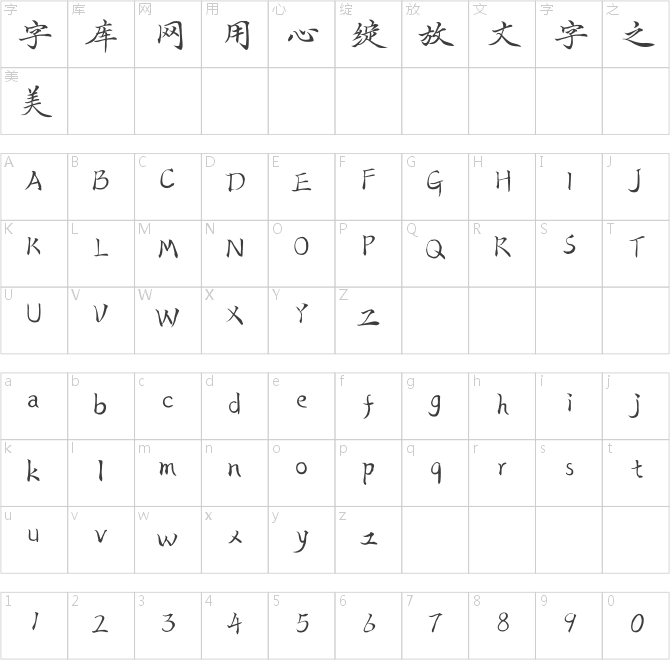
字體名稱: 漢儀常江小楷
漢儀常江小楷
漢儀常江小楷介紹
“漢儀常江小楷” 是由西安書法家協會會員、漢儀簽約字體設計師常江所書寫創作的一款書法字體。常江不僅擅長書法,還是一位資深媒體人,他是微博2019十大影響力書法博主,曾獲得微博首屆手寫大賽冠軍。他的書法傳播范圍廣,在微博、小紅書、抖音、B站等各大社交平臺上都非常受歡迎。
“漢儀常江小楷” 充分還原了書法作品的字形特點,細節表現十分完整。可廣泛用于海報、品牌和媒體等宣傳方面的使用。
筆勢靈秀飛動
“漢儀常江小楷” 的整體態勢均向右上方傾斜,字形氣勢整齊統一,增強了其排版效果的節奏感。
結構勁健灑脫
“漢儀常江小楷” 靈秀飛動,不同漢字結構的字面差異較大。從間架結構來講主要有三種情況:上展下收、上收下展和中間伸展。雖然是楷書,卻有著行書的行氣暢達、富于變化,遒美妍麗中透出勁健挺拔。
“漢儀常江小楷” 風格飄逸,字體內收外放,外部筆畫舒朗。以“更”、“皮”和“我”為例,中宮較為緊密,撇捺略顯張揚。
筆畫俊秀而不失張力
“漢儀常江小楷” 的線條流暢有彈性,筆畫遒勁俊雅富有張力,字體空間渾圓飽滿,展現出了卓爾不凡的氣勢。
“漢儀常江小楷” 在部分筆畫銜接處有留白,給予了字體與眾不同的透氣感和呼吸感。這使字體氣息更加流暢,更加具有生命力。
中西文匹配
“漢儀常江小楷” 的西文同樣用毛筆書寫,融入了中文書法的手寫方式。筆觸豐富,運筆流暢,手寫感強,中西文的搭配和諧統一。
排版效果
“漢儀常江小楷” 有著中宮收緊、筆畫舒展的字體特點,因此在豎排時會有更好的展示效果。字體的風格古典雅致,適用于詩歌、書信短文的排版,以及文化、商業類品牌的宣傳包裝設計。